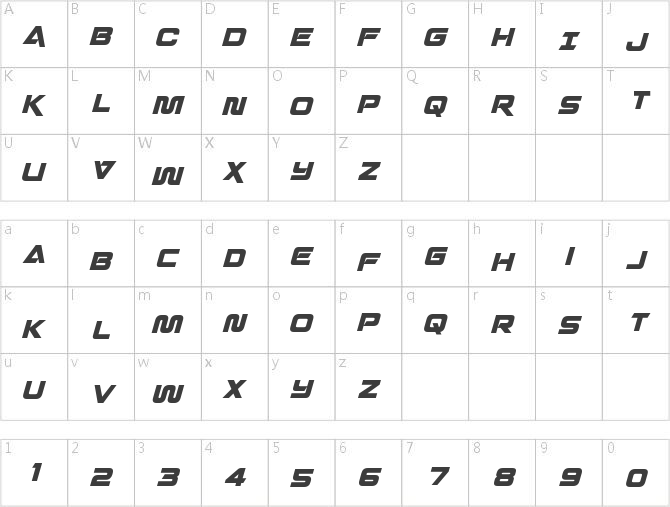
Quark Storm Condensed Italic
Quark Storm Condensed Italic介绍
Quark Storm Condensed Italic字体字库是一款让人赏心悦目、百看不厌的英文字体,适合各类广告和产品包装设计应用,字体大小0.02MB,格式为ttf字体,上传用户是 造物设计师,作者/版权方为未知